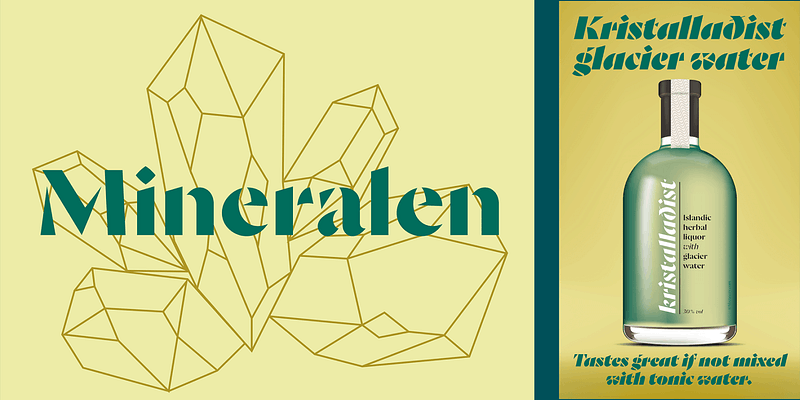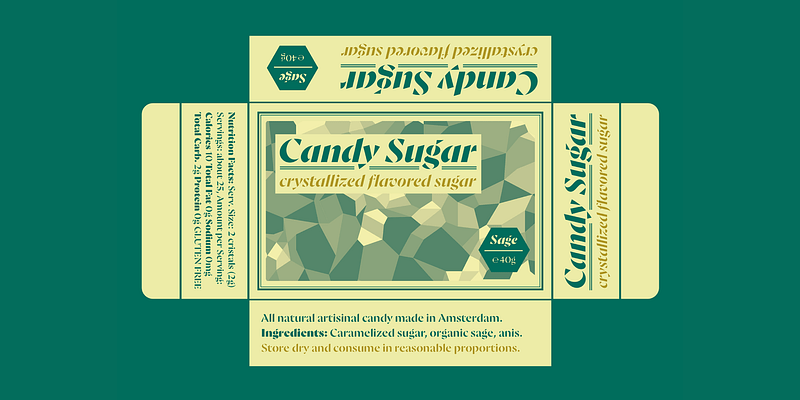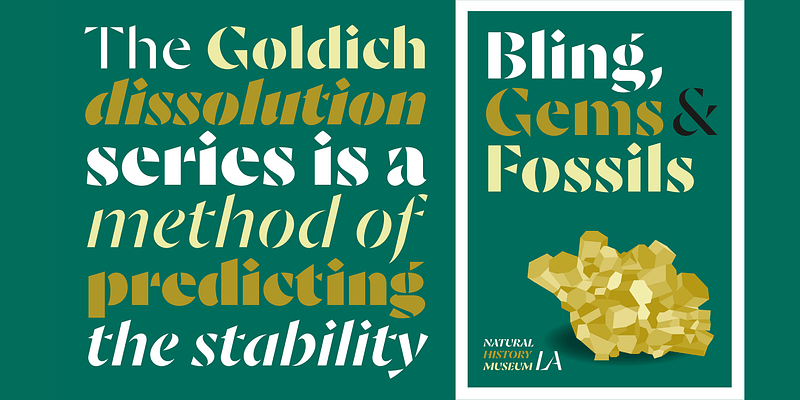
과학에서 Goldich 시리즈는 지구 표면의 광물의 풍화 속도를 예측하는 방법입니다. 1938년 Samuel Goldich는 가장 먼저 결정화되는 광물이 가장 먼저 풍화작용을 겪는다는 사실을 발견했습니다. 서체에서 Goldich 시리즈는 예리하게 잘린 모양으로 결정화된 문자 형태를 가진 서체 패밀리입니다. 몇 년에 걸쳐 Jasper de Waard는 이탤릭체를 더한 5개의 두께로 구성된 시리즈를 만들었습니다. 문자의 얇은 부분은 다양한 정도로 풍화되어 큰 크기에서 돋보일 수 있는스텐실 문자를 형성합니다. Goldich의 각진 디스플레이 특성은 전체 대문자 설정에서 특히 두드러집니다. 더 작은 대소문자 혼합 단락, 특히 이탤릭체는 모든 텍스트에 우아한 생기를 더합니다. 그러나 Goldich의 독특하고 장식적인 특성이 기능이 풍부한 패밀리가 아니라는 것을 의미하지는 않습니다. 100개 이상의 언어를 지원하는 글꼴에는 a, g, &의 대체 형태, 대/소문자 구분 구두점, 다양한 숫자, 분수 및 합자와 같은 세련된 타이포그래피를 위한 OpenType 기능이 완비되어 있습니다. 다음 아이덴티티 또는 광고 프로젝트에 사용하거나 간판 및 스텐실의 재미를 위해 사용하십시오.